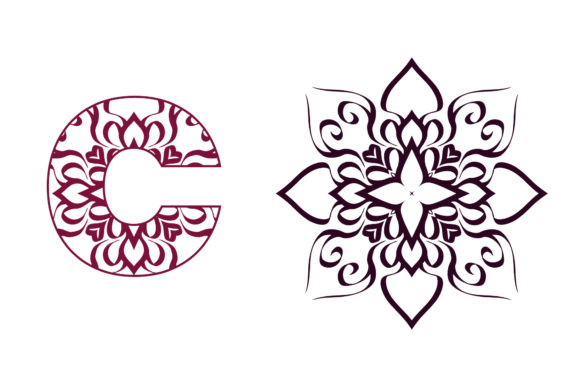
Mandala Font Alphabet C Art
適切なデザイン要素を見つけるのは難しい場合がありますが、Mandala Font Alphabet C Artは作品を即座に引き立てる優れたコレクションを提供します。
POD(オンデマンド印刷)製品、結婚式の招待状、またはソーシャルメディアのグラフィックを作成している場合でも、Mandala Font Alphabet C Artは理想的です。